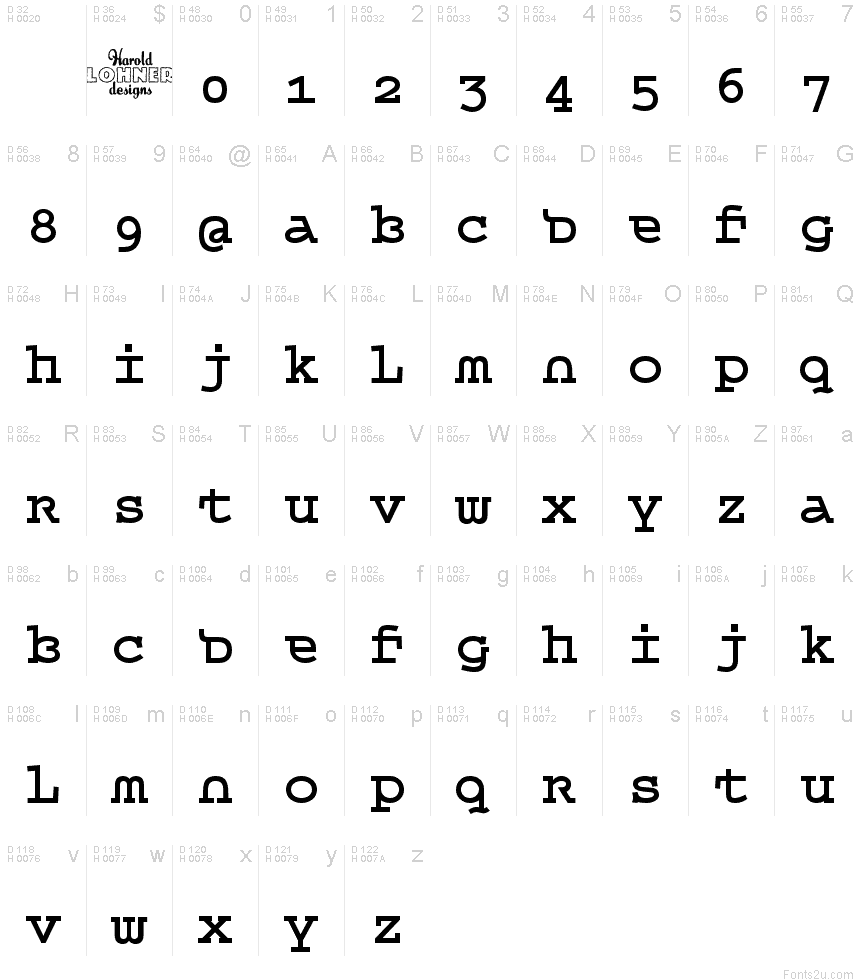
Queer Theory di Harold Lohner è un font display futuristico gratuito, caratterizzato da curve corpose, terminali netti e un'irriverente attitudine digitale di fine anni '90. Le lettere appaiono allo stesso tempo pesanti e vivaci, mescolando ampi tratti rotondi con giunzioni nette e piccoli uncini che rendono il ritmo giocoso anziché severo.
È ideale per flyer di club, copertine di zine, titoli di poster, cartelli e sperimentazioni su loghi in cui un font gratuito richiede carattere senza scivolare nell'eccentricità. Grazie alle forme ampie, scure e ricche di insolite curvature, si inserisce perfettamente in frasi brevi, copertine e progetti di branding che cercano un'estetica retro-tech.